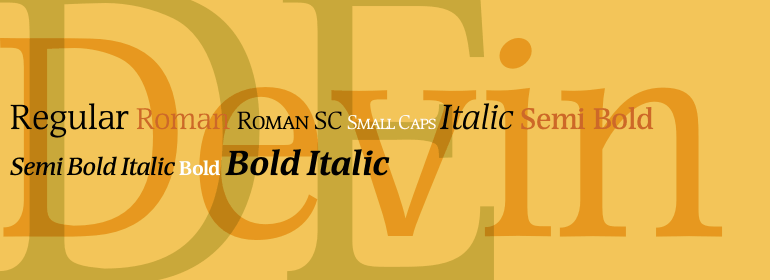
Devin™
字体品牌: Linotype(Monotype) 设计师:Luin,Franko 字体分类:衬线体、正文字体 字体属性:外文 字符集:Unicode 发布时间: 2018
Devin主要是为了广告行业而设计,它确实是一款漂亮的标题字体,不是吗?并且您应该看到它是一款多么漂亮的正文字体啊!在创作该字体时,我并没有想其他字体,但是现在我可以找到几款与之相关的字体。这让我想起了egyptienne(粗衬线体),但我并没有这个计划。
Devin这个名字取自我的出生地。亚得里亚海的北部海岸上有一座同名城堡(甚至在Rilke的《Duino elegies》中也有——Duino是同一座城堡的别称)。在斯洛伐克多瑙河的高处,离首都布拉迪斯拉发不远的地方,也有一座名为Devin的城堡废墟。
Devin发布于1994年。
Devin is designed mainly for the benefit of the advertising industry, and it surely is a nice typeface for headings, isn't it? And you should see what a nice body type it makes! I had no other typeface in mind when working with it, but I can now find several typefaces it is related to. It reminds of the egyptienne group, but I did't really plan that.
The name Devin is taken from my birth region. There is a castle with that name on the northern Adriatic coast (known even from Rilke's Duino elegies - Duino is another name of the same castle). A castle ruin called Devin, too, can be found on a height above the Danube in Slovakia, not far away from its capital Bratislava.
Devin was released in 1994.